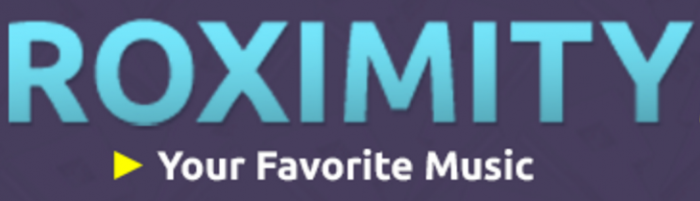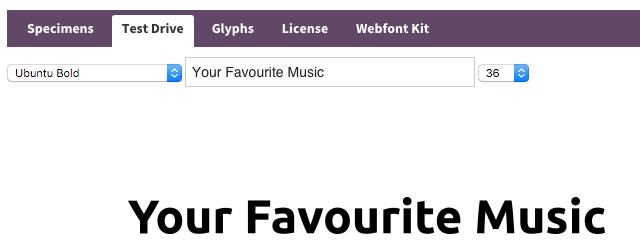
Schriftart gesucht
Die Museo kann es nicht sein. Da unterscheidet sich fast jeder Buchstabe vom gesuchten Schriftzug. Ich denke, dass es sich um die Ubuntu Bold handelt.
Ich denke du denkst richtig  :-)